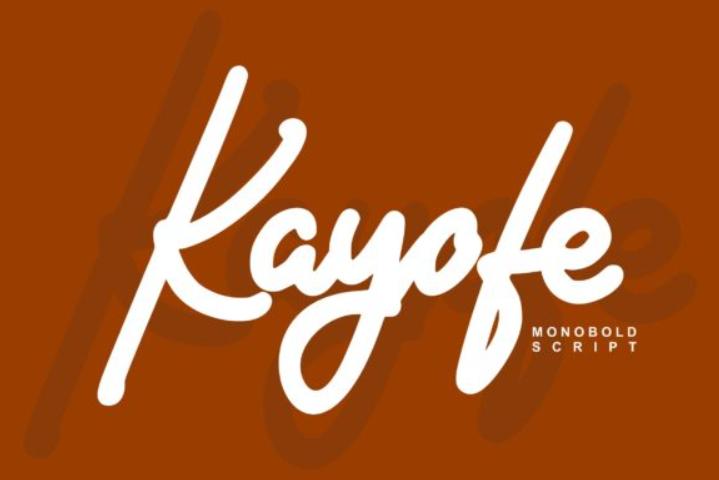
[Creativefabrica] Kayofe Font (FannanStudio)
Kayofe - прекрасный и неподвластный времени рукописный шрифт. Это лучший выбор для создания привлекательных логотипов, брендов и цитат. Каждая буква имеет уникальный и красивый штрих, который оживит ваш дизайн!